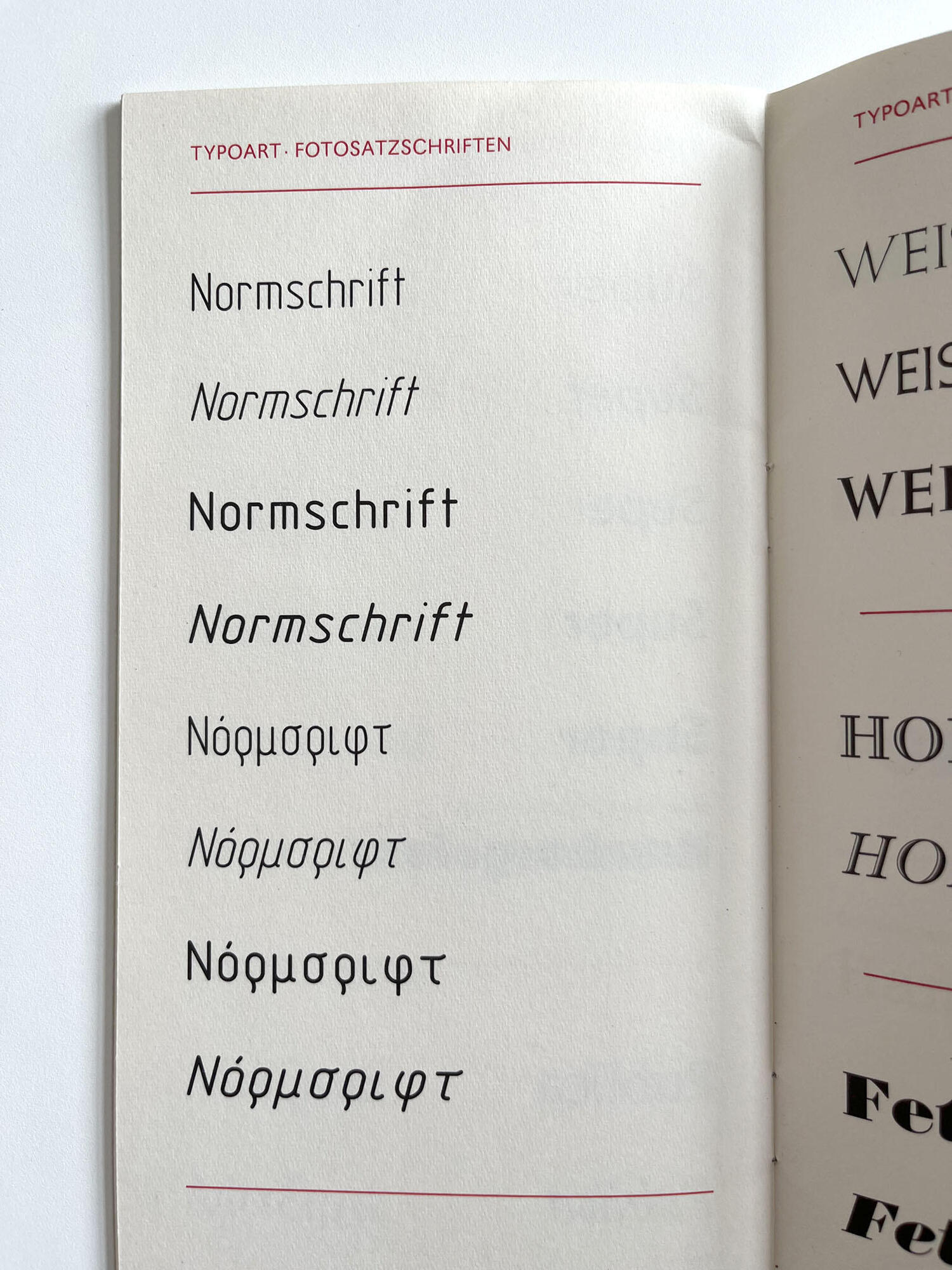
Ich vervollständige ja gerade die Schrifteinträge zu Typoart. Eine Schrift, zu der ich aber überhaupt nichts finden kann, ist die RGW Type von Elsner+Flake. Es heißt dort nur »Typoart 1984«. Im Buch Fotosatzschriften werden eigentlich die ganzen Typoart-Schriften der 1980er-Jahre dokumentiert, aber auch dort taucht die Schrift nicht auf. Weiß jemand mehr?
(RGW verweist auf den Rat für gegenseitige Wirtschaftshilfe.)
In den Fotosatz-Ordnern aus den 1980ern inkl. Nachtrag von 1990 findet sich nichts. Und auch in der Firmenchronik 1945–1985 gibt es lediglich ein Bild mit Bezug zum RGW aber keine Erwähnung einer entsprechenden Schrift.
Optisch sieht die RGW Type aus wie die Normschrift von Typoart (die es auch in griechisch gab).